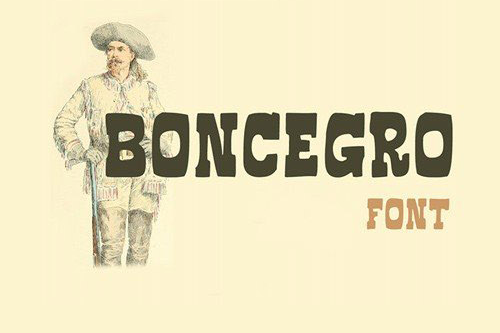
A Boncegro Font é uma elegante slab serif que oferece um toque sofisticado para projetos digitais e impressos. Seu design fluido e minimalista se destaca pela harmonia entre simplicidade e elegância, tornando-a perfeita para aplicações de logotipo ou letras em grandes tamanhos. A Hamilton criou essa fonte meticulosamente para oferecer um conjunto de caracteres bem balanceado que é tanto versátil quanto bonito. Ideal para design gráfico, a Boncegro traz um toque único e sofisticado às suas criações digitais. Suas linhas fluidas e o design compacto permitem uma execução perfeita, garantindo consistência em seu estilo e harmonia entre diferentes seções de texto. Além disso, sua facilidade de uso e capacidade de personalização fazem dela um recurso indispensável para designers gráficos profissionais ou amadores buscando adicionar um toque de sofisticação a suas produções digitais.